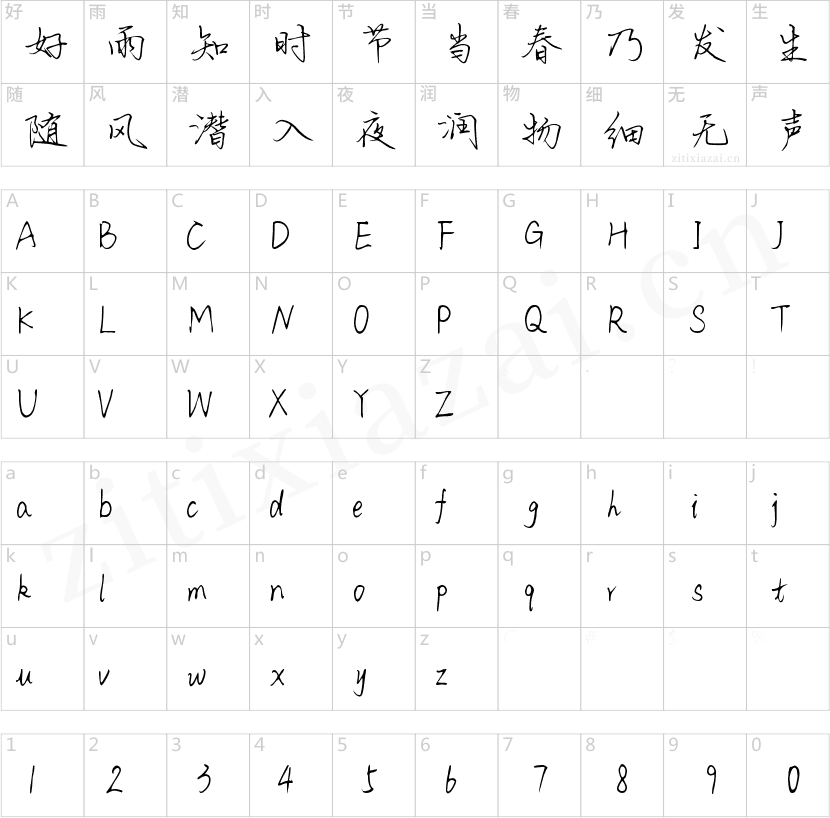
Aa远赴惊鸿宴,这款字体结构工整、笔画清晰,兼顾美观与易读性,适用于标题、正文、海报、包装、LOGO 等多种场景。字形优雅稳定,风格百搭耐看,适配日常排版与创意设计,让文字呈现更舒适、更具质感。Aa远赴惊鸿宴一笔一画,皆是细节,以均衡的比例、流畅的线条打造舒适视觉体验,字形端正大气,风格简约现代。无论是商业设计、品牌宣传还是日常排版,都能轻松驾驭,让文字更有格调与力量。Aa远赴惊鸿宴字体下载。
Aa远赴惊鸿宴是一款非常具有艺术性的字体,它的设计灵感来源于对古典艺术的研究,同时又融入了现代字体设计的元素。字形优美,笔画粗细变化自然,给人以大气、典雅的感觉。Aa远赴惊鸿宴是一款既传统又现代的字体,它的设计充满艺术感,美观大方,实用性也非常强。无论是对于设计师还是对于普通读者来说,都是一种非常不错的字体选择。Aa远赴惊鸿宴适合用于具有艺术感的场合,比如海报、宣传单张、书籍封面等。由于其字形流畅且具有动态感,也适合用于大量的文本排版,如报纸、杂志等。